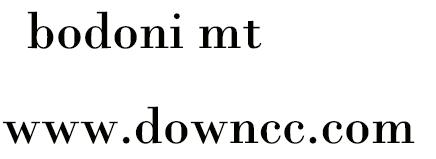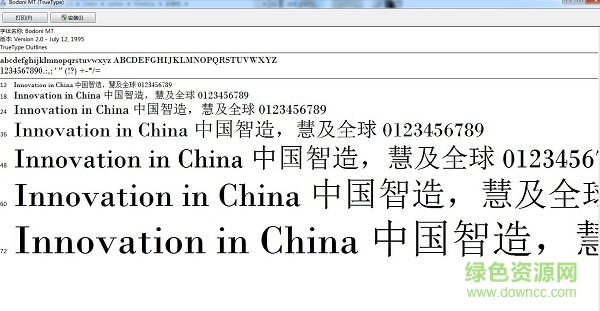
bodoni mt 普通字體是一款常規(guī)襯線字體,筆法細(xì)膩,線條粗細(xì)分明,識(shí)別性高,具有較強(qiáng)的現(xiàn)代氣息,適合雜志、書籍、海報(bào)的設(shè)計(jì)應(yīng)用,有需要者快來下載吧!
【老式字體】
往往有襯線,反映出傳統(tǒng)字體設(shè)計(jì)的特征,老式字體字母往往會(huì)有傾斜的軸線,這是鐫刻字體的鑿子類工具所特有的痕跡。
【過渡性字體】
過渡性字體也有襯線,但字母中粗細(xì)線條的反差沒有老式字體那么明顯,而且其軸線也趨于垂直;字體本身看起來更清晰,具有手工繪制的特色。
【現(xiàn)代字體】
設(shè)計(jì)趨于清晰簡(jiǎn)潔,為迎合現(xiàn)代特征,字體設(shè)計(jì)被簡(jiǎn)化,襯線逐漸被去除,線條也不再有粗細(xì)之分,干凈利落,更具機(jī)械繪制的特點(diǎn)。